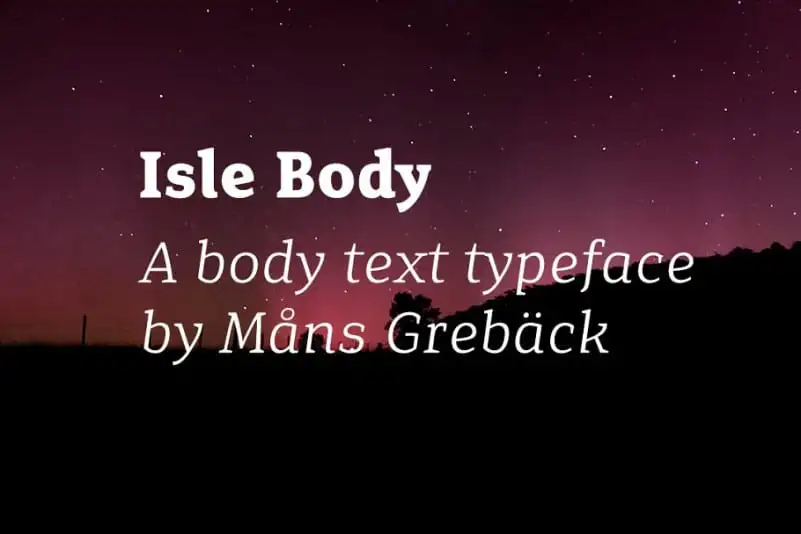
Aisle Body é uma famosa fonte serif para textos do corpo que traz uma sensação suave e confiante. Desenhada pelo talentoso designer Mans Greback durante os anos de 2018 e 2019, Isso se tornou um verdadeiro tesouro para designers gráficos em busca de uma fonte elegante para textos do corpo. A Isle Body oferece espaçamento generoso e uma leveza que faz dela uma escolha perfeita para projetos que exigem tanto qualidade quanto personalidade. Com seu design casual e tranquilo, essa fonte é ideal para o texto do corpo e para configurações de tamanho tipo menores. Escolha a Isle Body se estiver buscando um padrão elegante e funcional para seus próximos projetos gráficos, que garantem uma experiência visual agradável sem comprometer o bom olhado à legibilidade.